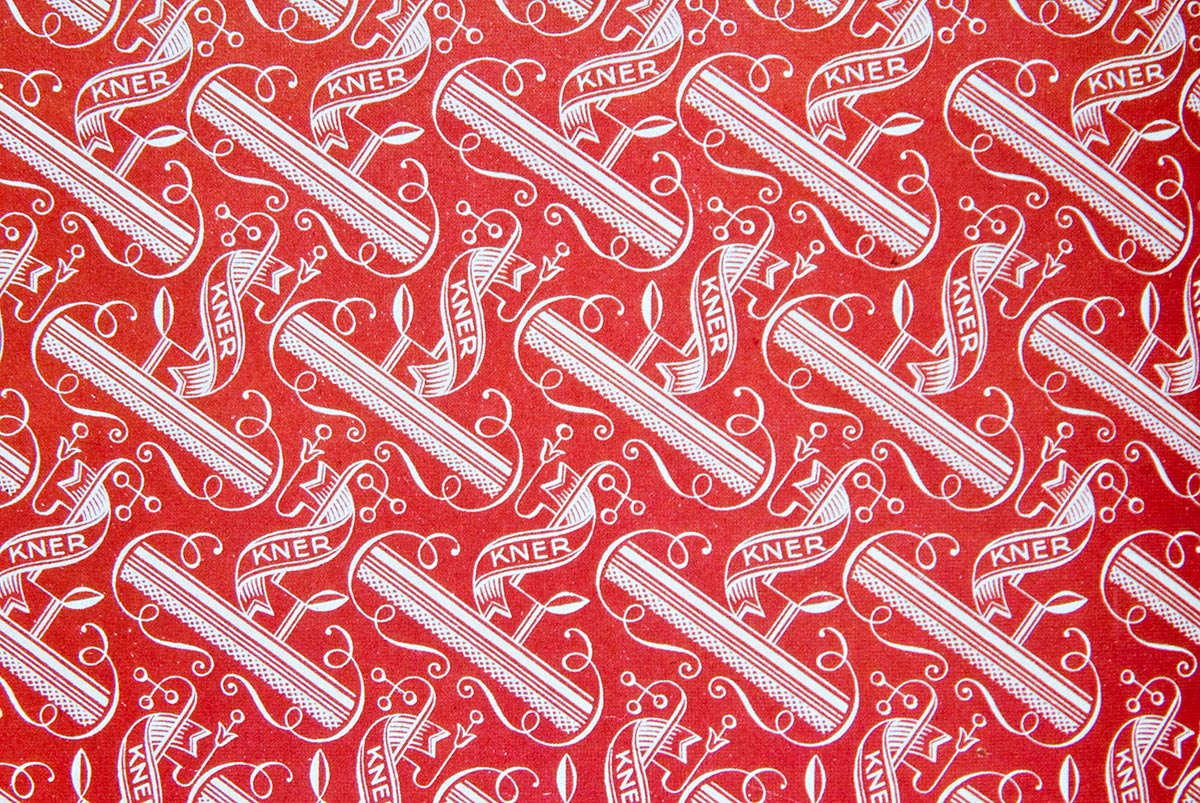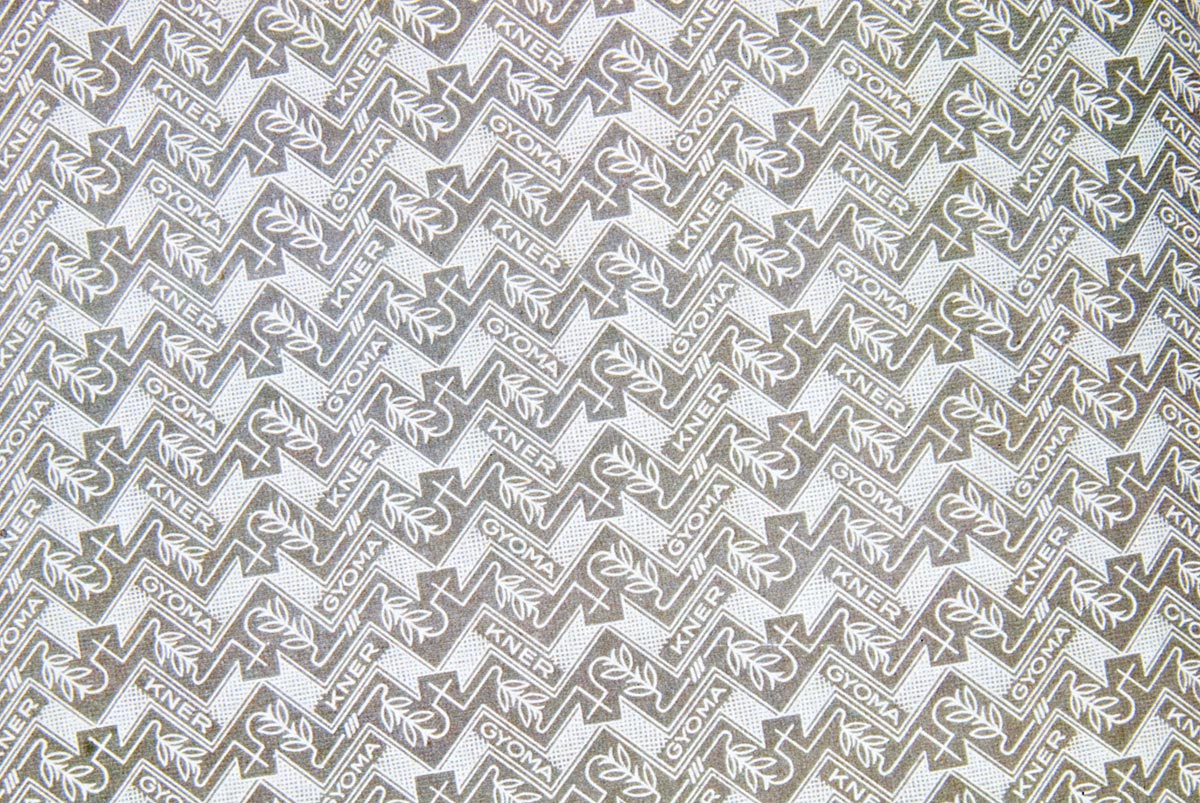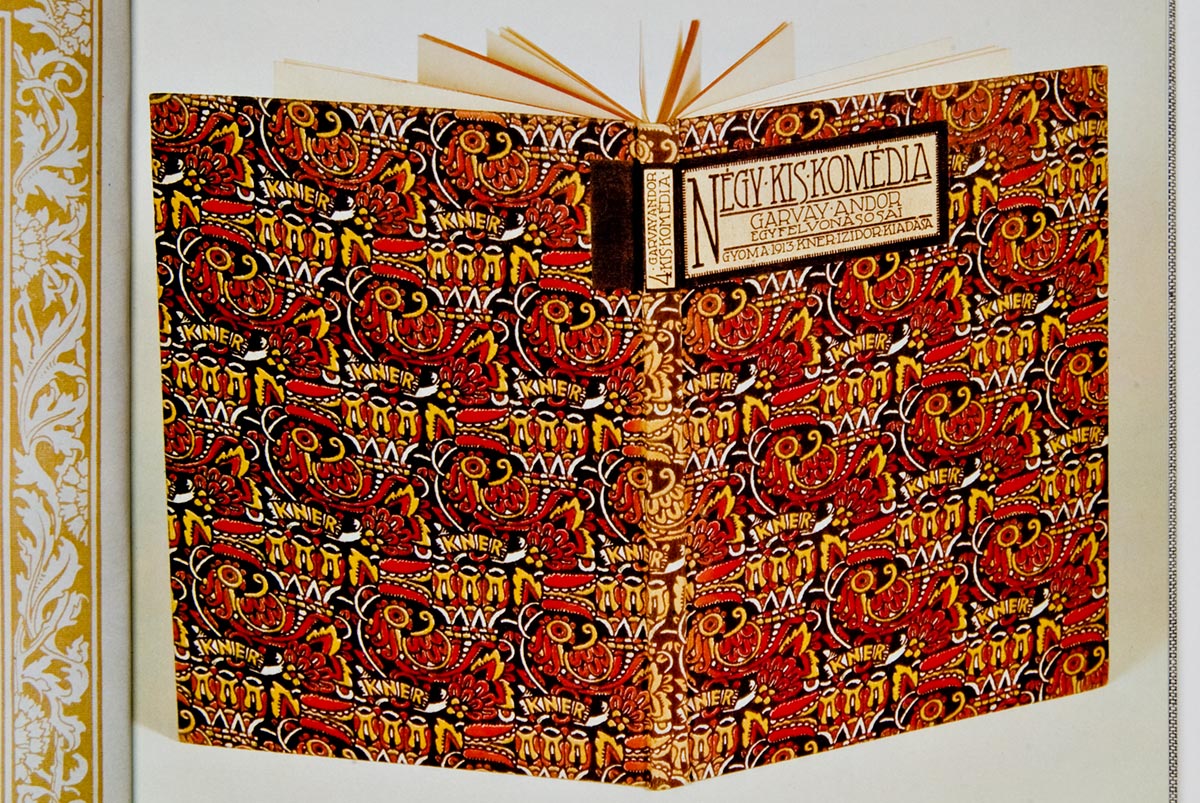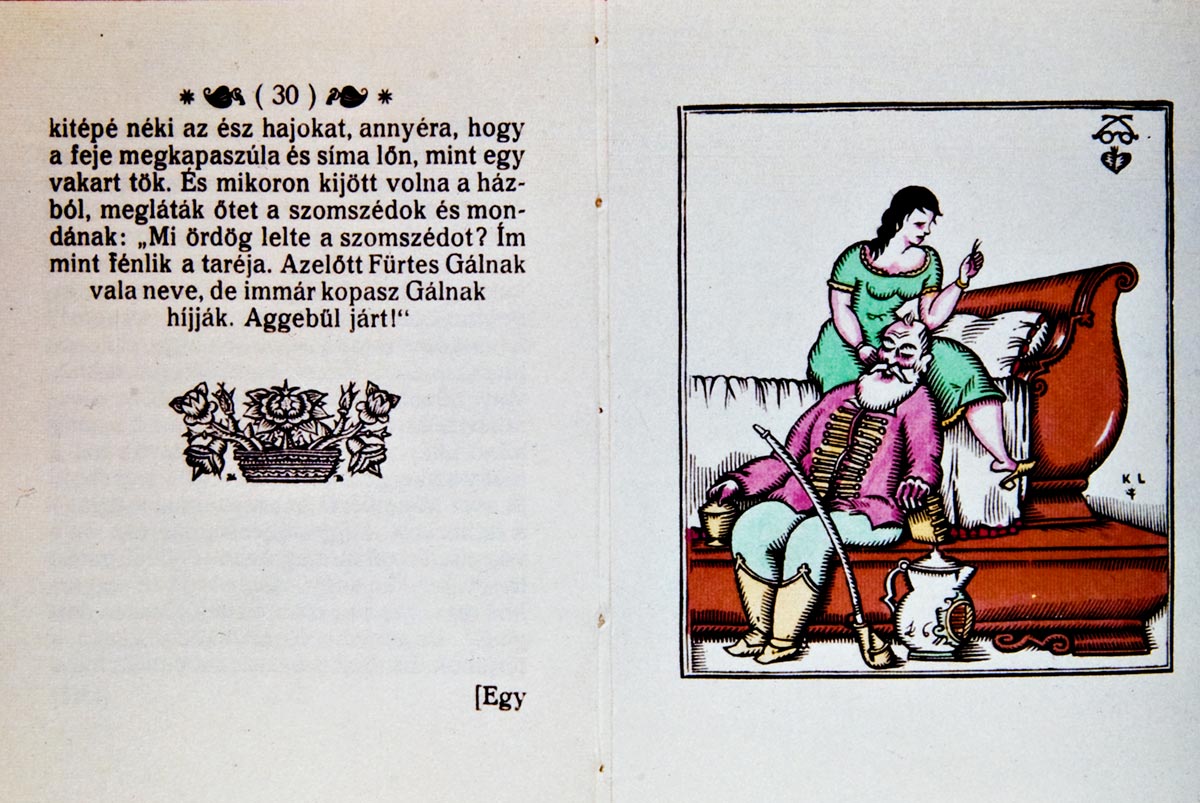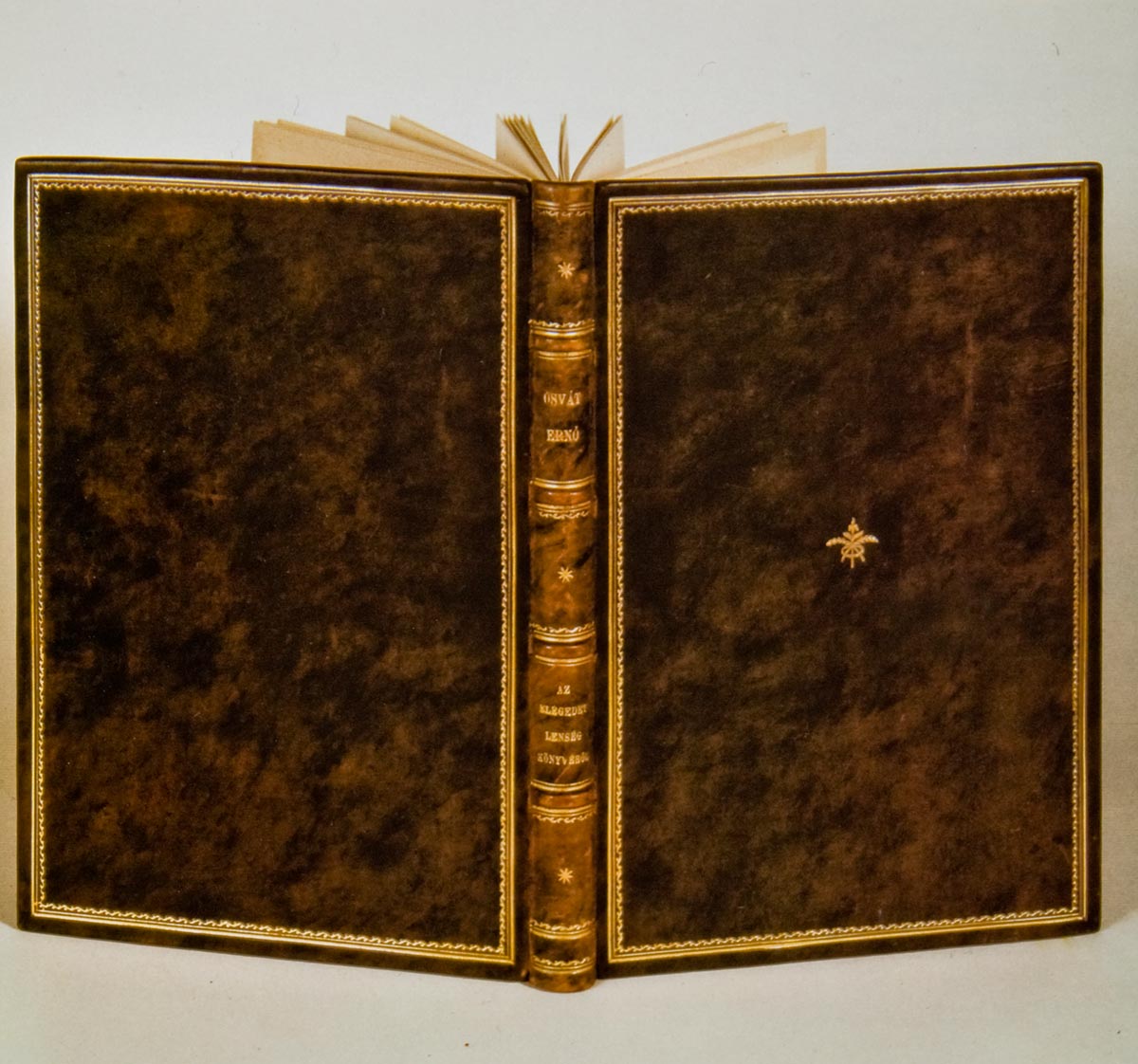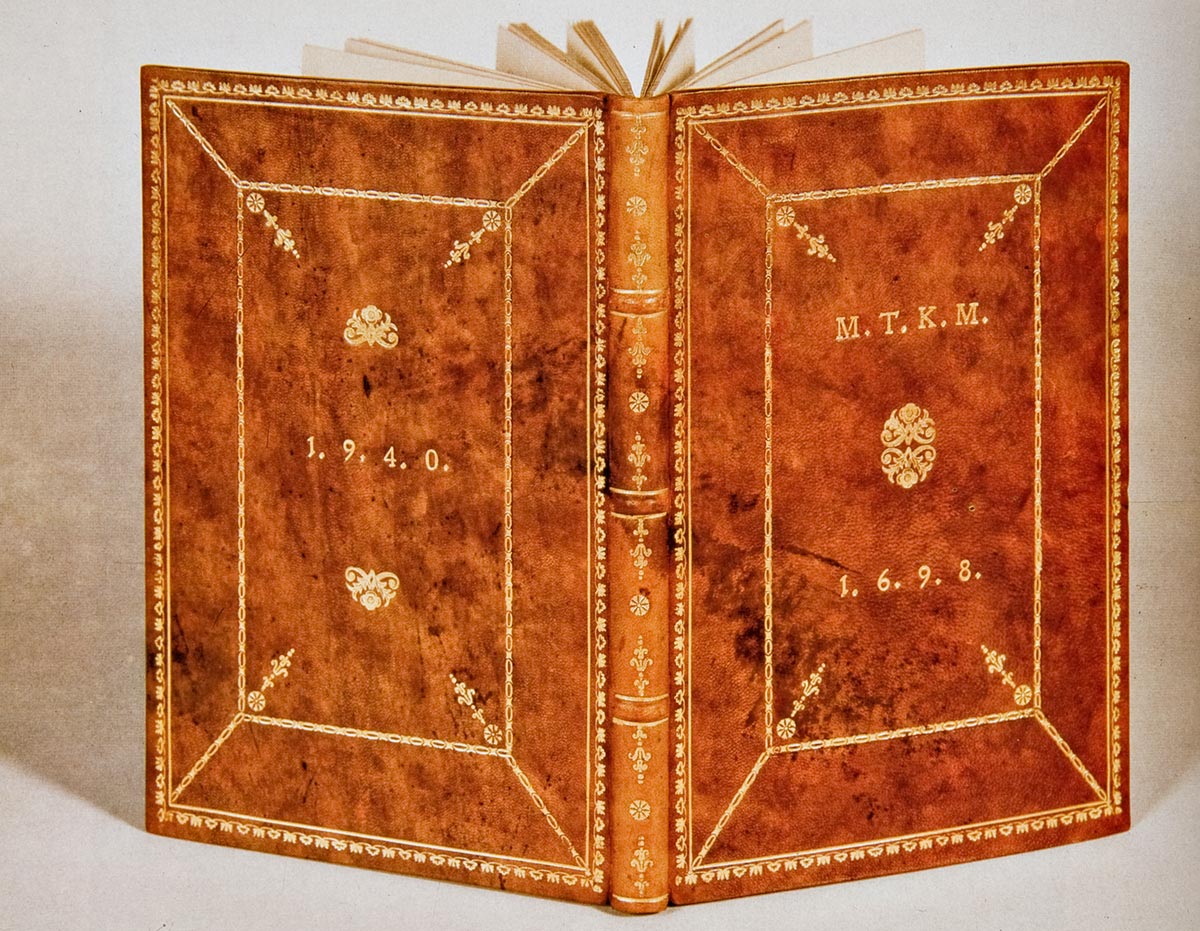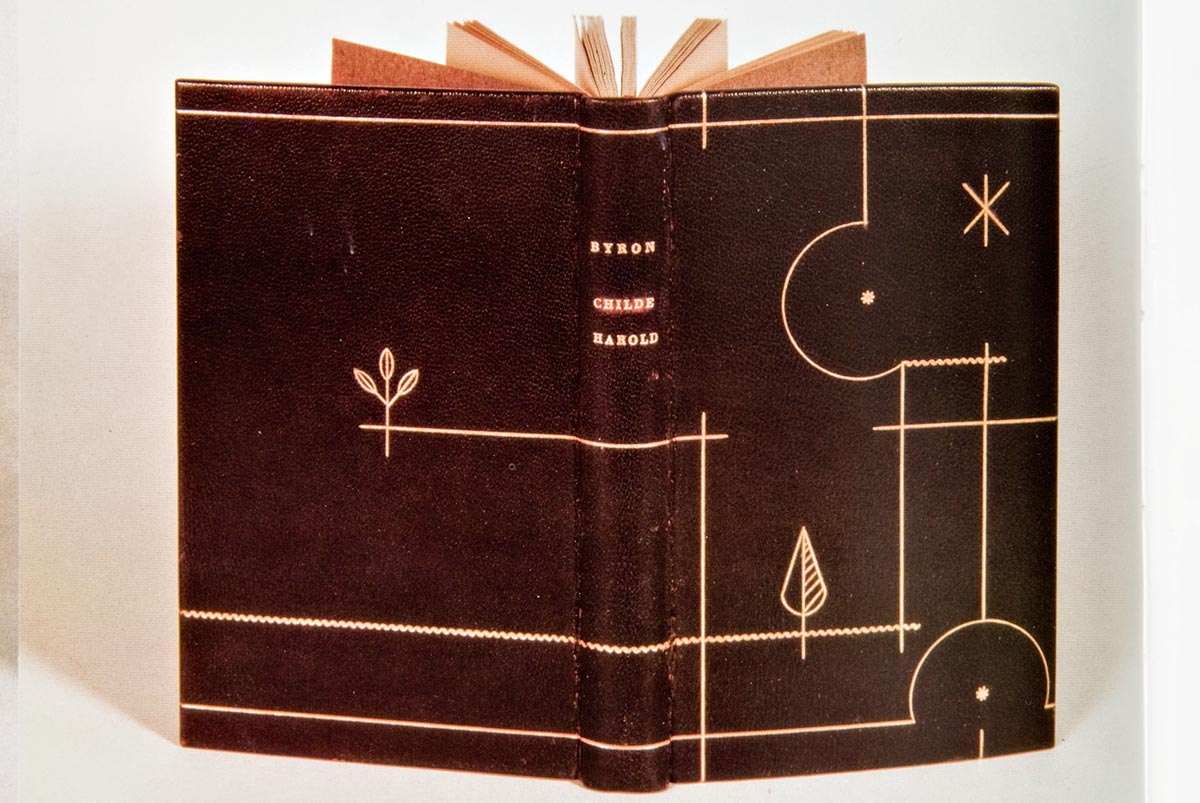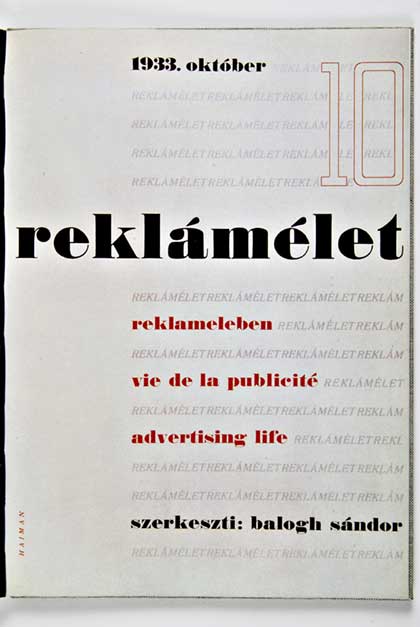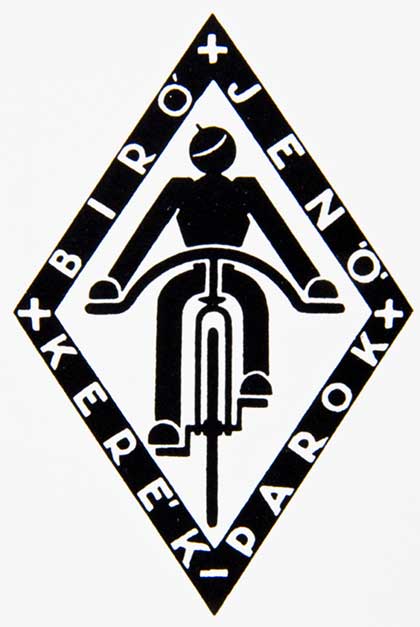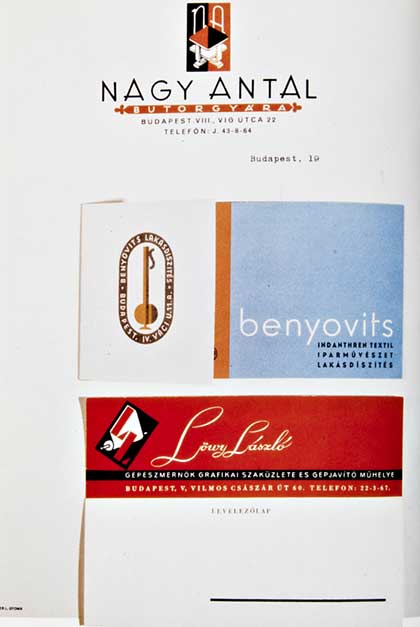
Kner, une famille d’imprimeur-éditeur magyare | 1882-1944 | 2/2
Reliure cuir avec dorure par Erzsébet Kner, 1924
Reliure doré pour un hommage à l’œuvre de Kis Miklós, Le Totfalusi
1940, réalisé par Erzsébet Kner.
Jaquette de livre, conception Kner Imre, 1941
Pour un Roman de Izidor Kner, Jaquette dessiné par Gergely Tibor et mis en page par Haiman György
dessin par Gergely Tibor
Jaquette de livre, 1935
Reliure doré par Erzsébet Kner pour un livre de Osvát Ernö
Signet dessiné et typographié par Kozma Lajos en 1925
Deux couvertures décorés par Kozma Lajos et mis en page par Kner Imre
Décoration pour une reliure par Kozma Lajos,1921
Deux gravures sur bois de Kozma Lajos, 1920
Couvertures de ‘contes pour enfants’ de Balázs Béla illustré par Kozma Lajos et Lesznai Anna dessiné et illustré par l’auteure elle-même.
Couverture d’Almanach dessiné par Kozma Lajos, 1919
Jaquette de livre dessiné et maquettée par l’auteure elle-même, Lesznai Anna, 1918
Jaquette de livre maquetté par Kozma Lajos, 1917
Pour le Livre des Livres, une page, maquette de Kner Imre et frise décorative par Geiger Richárd
Dessin décoratif de Örkényi István pour un livre réalisé par Kner, 1913
Maquette constructiviste pour une jaquette de livre par Kner Imre, 1907
Kner Izidor, éditeur, maquettes de couverture par le jeune Kner Imre, 1906
Travaux d’impression de ville, maquettes d’Albert Kner, 1930-1935
Graphismes de Kner Albert, 1933
Fond d’agendas, graphisme de Kner Albert, 1930
Couverture de magazine ‘la vie de la Réclame’, maquette de Haiman György, 1933
Carte de vœux pour 1930 par Kozma Lajos